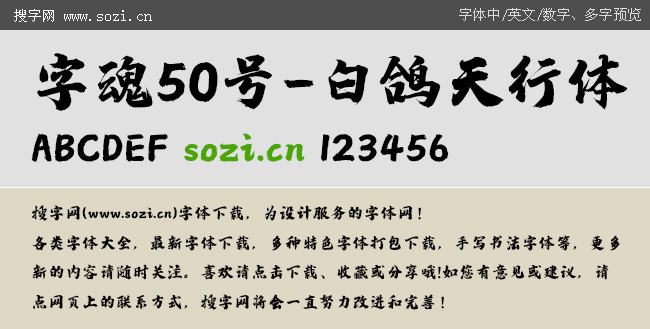
字魂50號-白鴿天行體
搜字網(wǎng)提供一款字魂50號-白鴿天行體中文字體下載,該字體是一款毛筆書法手寫字體,該字體包含6763個(gè)中文、字母、 符號和數(shù)字,具有大氣、穩(wěn)重、古典、中國風(fēng)、豪放、力量、手寫風(fēng) 的風(fēng)格,可以滿足您設(shè)計(jì)上的各種需求,該字體主要用于美食餐飲、健康養(yǎng)生、青春校園、活動(dòng)展會(huì)、電商促銷 等場景。